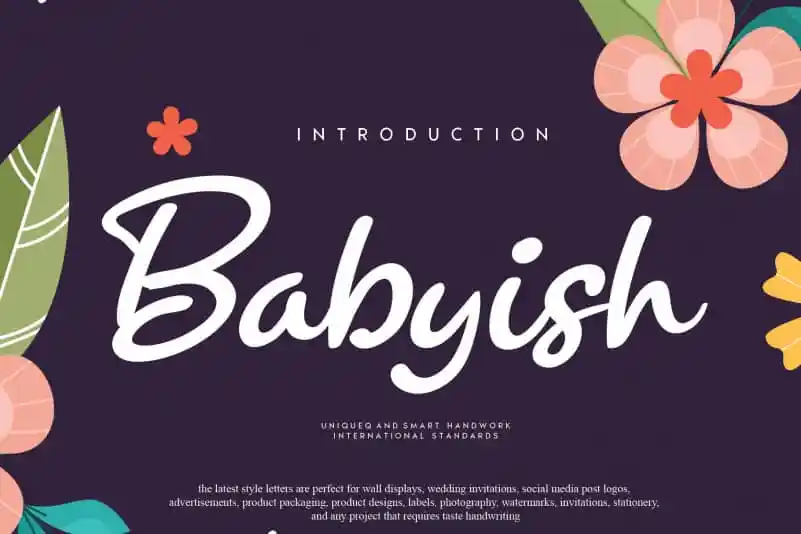
Babyish Script Font – Fonte Grátis
Babyish Script Font
Aqui está uma descrição em português para a página de download da fonte ‘Babyish Script Font’, seguindo as especificações fornecidas: Descubra Babyish Script Font, um handwritten font perfeito para aqueles que buscam uma aparição natural e envolvente em seus projetos digitais. Apropriada para trabalhos como logotipos, cartões de aniversário ou até mesmo artigos de blog, essa fonte é especialmente criativa, oferecendo um toque único ao seu design. Se você está procurando por uma fonte que transmita suavidade e delicadeza sem perder a personalidade, Babyish Script Font será perfeito. Suas letras fluidas e levementes trazem vida à sua produção, transformando-a em algo verdadeiramente especial. Ideal tanto para um estilo minimalista quanto para os mais elaborados, este é uma opção versátil que certamente se destacará. Com a Babyish Script Font, você encontra uma maneira de dar vida ao seu trabalho, transmitindo emoção e beleza de maneiras sutis e autênticas. Com sua elegância natural e seu toque encantador, esta fonte é um recurso gráfico indispensável para qualquer designer digital.